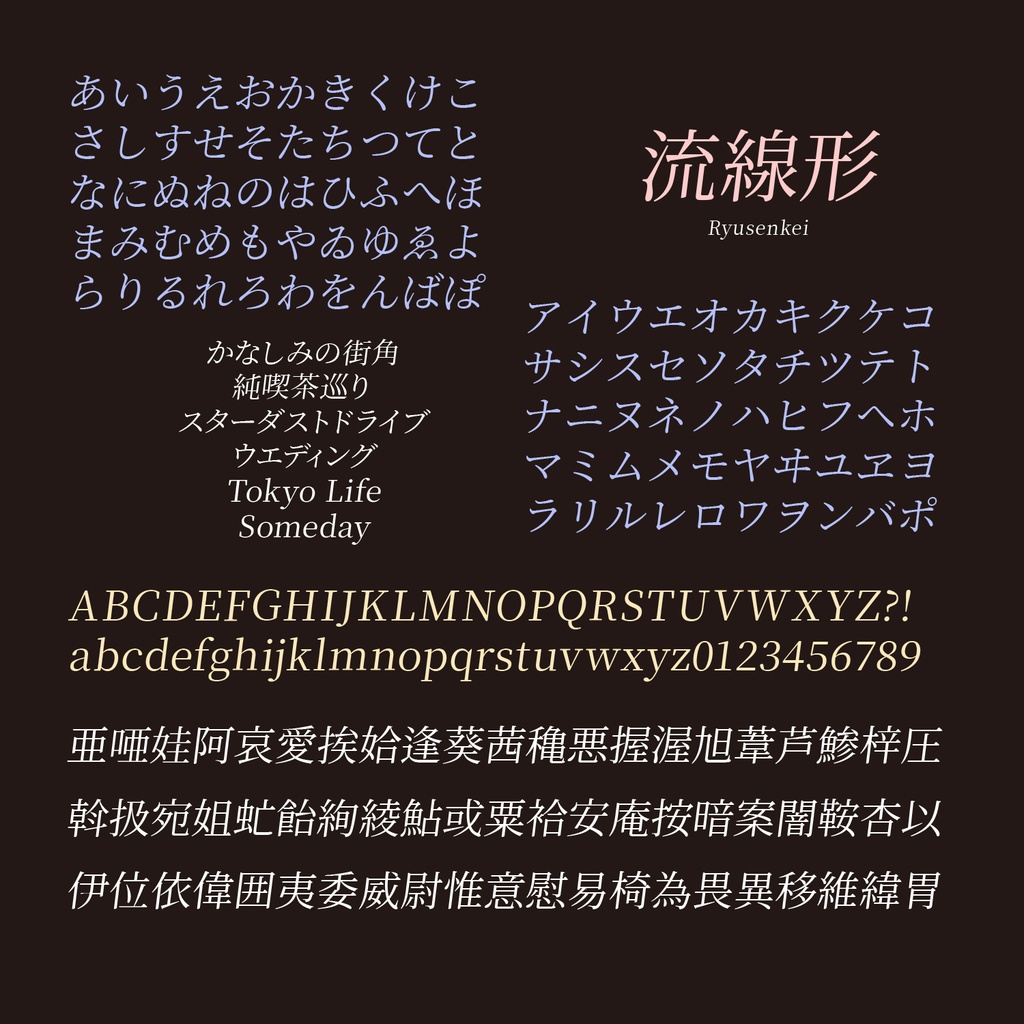
フリーフォント使用に当たって フォントをインストールして頂くとパソコンのワープロ、グラフィックソフトなどのアプリケーションを使って自由にデザイン、印刷することができます。個人利用・商用利用にかかわらず、無償で使用することができます。当フォントはSIL Open Font License 1.1のライセンスに準じます。 【流線形の概要】 流線形は以下の派生フォントです。 「源ノ明朝 (Source Han Serif)」 【書体コンセプト】 源ノ明朝の素晴らしさを活かした斜体の横組み用明朝体です。 また先端が丸くなって、やわらかい雰囲気になっています。 【ライセンス】 このフォントのライセンスは、 フォントは以下のライセンスに準じます。 SIL Open Font License 1.1 の説明は同梱の LICENSE_OFL.txtをお読み下さい 日本語訳は以下になります。 https://osdn.jp/projects/opensource/wiki/SIL_Open_Font_License_1.1 頒布元 フロップデザイン https://www.flopdesign.com/ 改変元 流線形は以下のフォントを改変して制作しました。 制作に関わる全ての方に深くお礼申し上げます。 源ノ明朝 (Source Han Serif) https://source.typekit.com/source-han-serif/jp/ ⚠️このフォントは自由に動画に使えるフォントです。ご利用の際は次のクレジットを入れていただけると、ものすご〜く喜びます! –––––––––––––––––––––––––––––– フォント:流線形 フリーダウンロード:https://flopdesign.booth.pm/items/6383865 –––––––––––––––––––––––––––––– Instagram ▶ https://www.instagram.com/flopdesign.font/ X ▶ https://twitter.com/flopdesign BlueSky ▶ https://bsky.app/profile/flopdesign.bsky.social